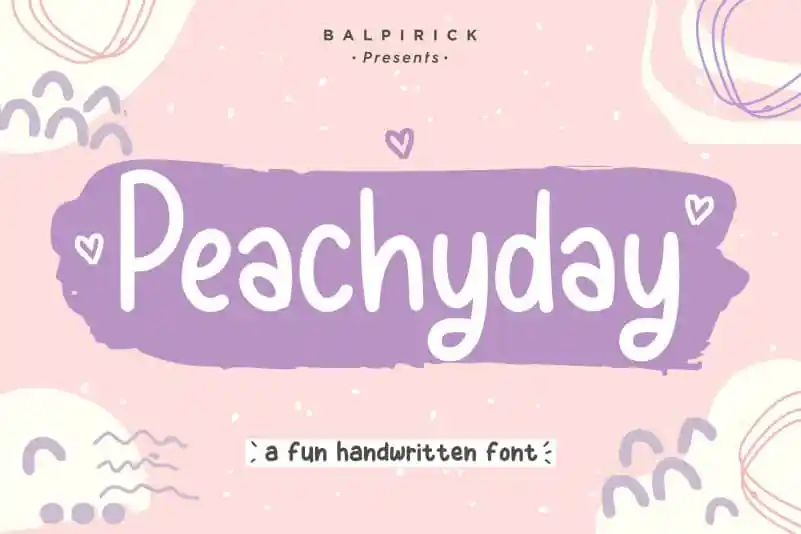
Peachyday Fun Handwritten Font – Download Grátis
A Peachyday Fun Handwritten Font é uma escolha perfeita para quem busca expressar alegria e simplicidade em projetos digitais. Seja você criando embalagens de produtos, estilizando logotipos, montando revistas ou até mesmo utilizando-a nas redes sociais, esse fonte traz um toque divertido e encantador à qualquer projeto. A Peachyday é perfeitamente adaptada para aprimorar o visual dos projetos relacionados ao casamento, oferecendo uma maneira elegante de decorar as mensagens que aparecem acima do background. Seja você criando um site, aplicativo ou até mesmo material impresso, essa fonte vai deixá-lo com aquele ar único e alegre que seu projeto merece. Com sua escrita curvilínea e entusiasmada, a Peachyday Fun Handwritten Font é uma excelente opção para expressar personalidade em qualquer formato de mídia digital ou impressão.